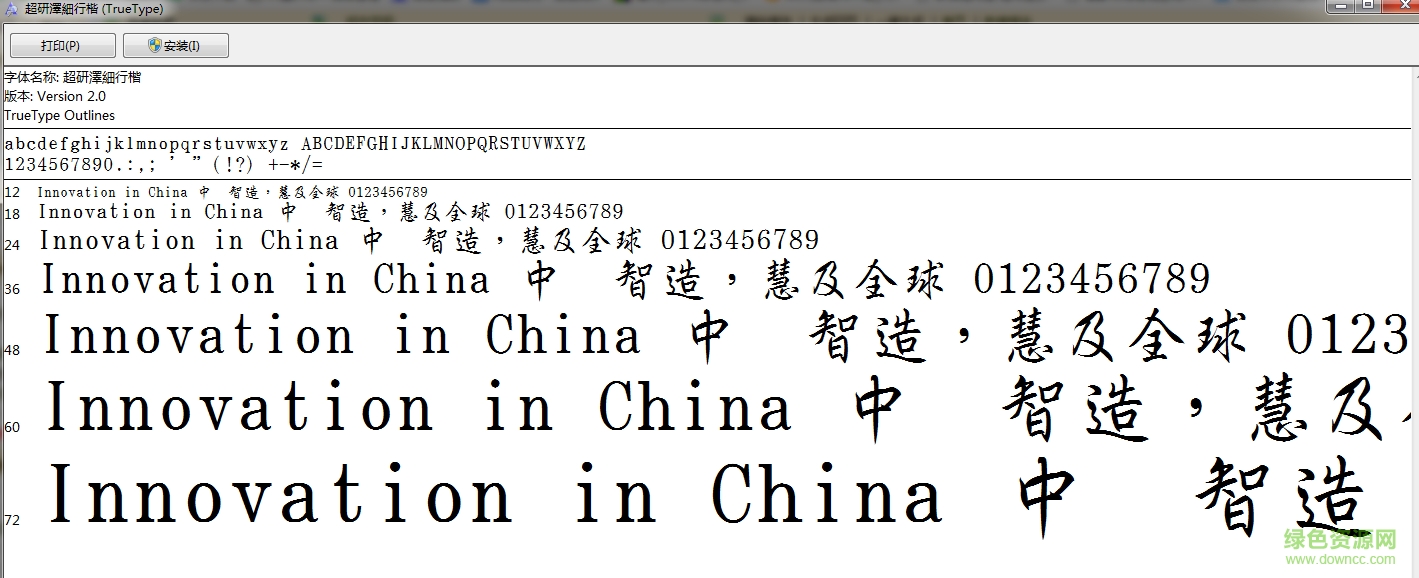
超研澤細(xì)行楷體繁體以楷體字為原形,對(duì)其進(jìn)行了相應(yīng)的處理,讓其字體更加的美觀,字形端正大方,整體風(fēng)格非常出色,并且字庫(kù)完整,可廣泛應(yīng)用于平面設(shè)計(jì)、廣告設(shè)計(jì)、報(bào)紙雜志、正文標(biāo)題等領(lǐng)域,喜歡的網(wǎng)友可免費(fèi)來綠色資源網(wǎng)下載收藏。